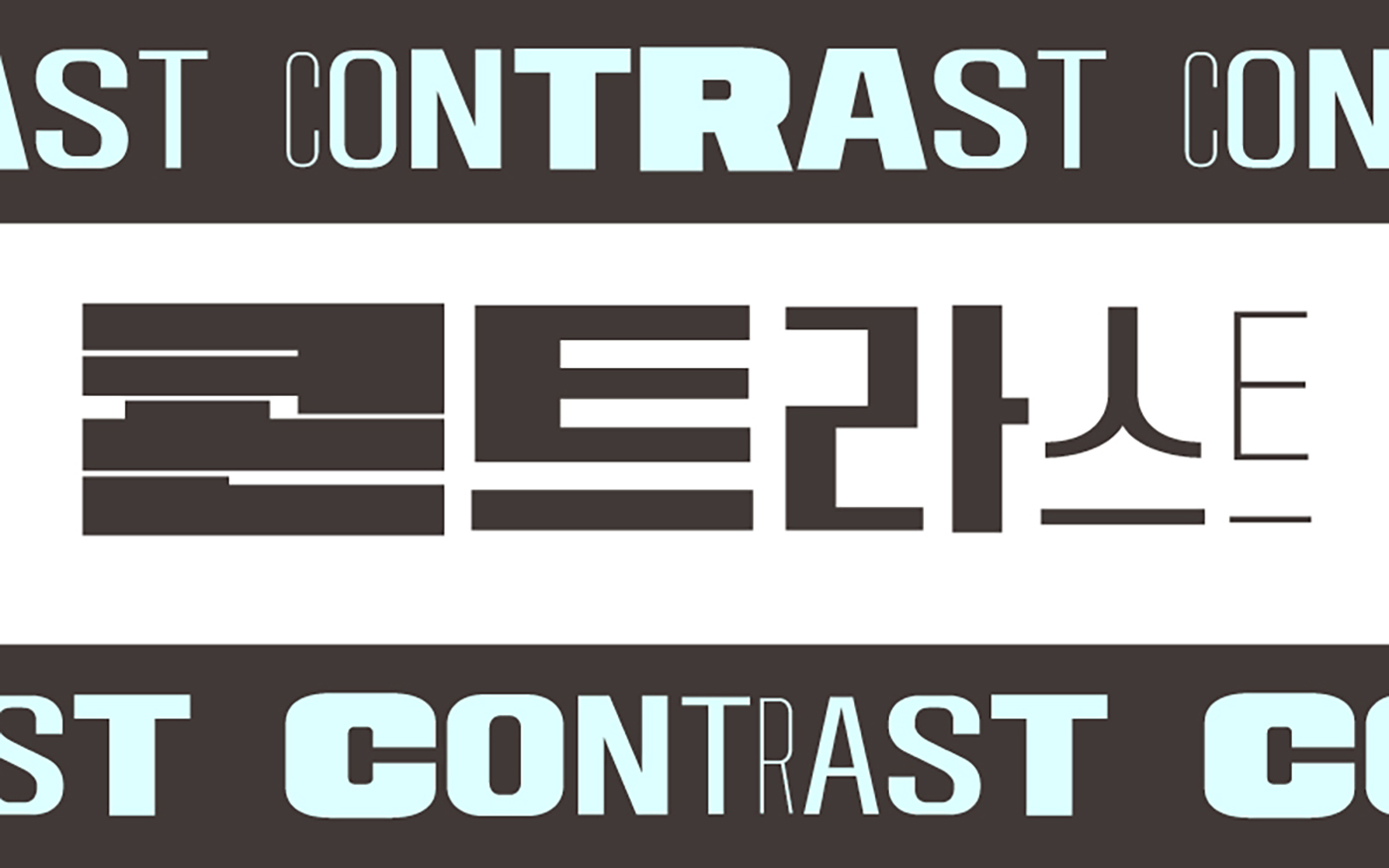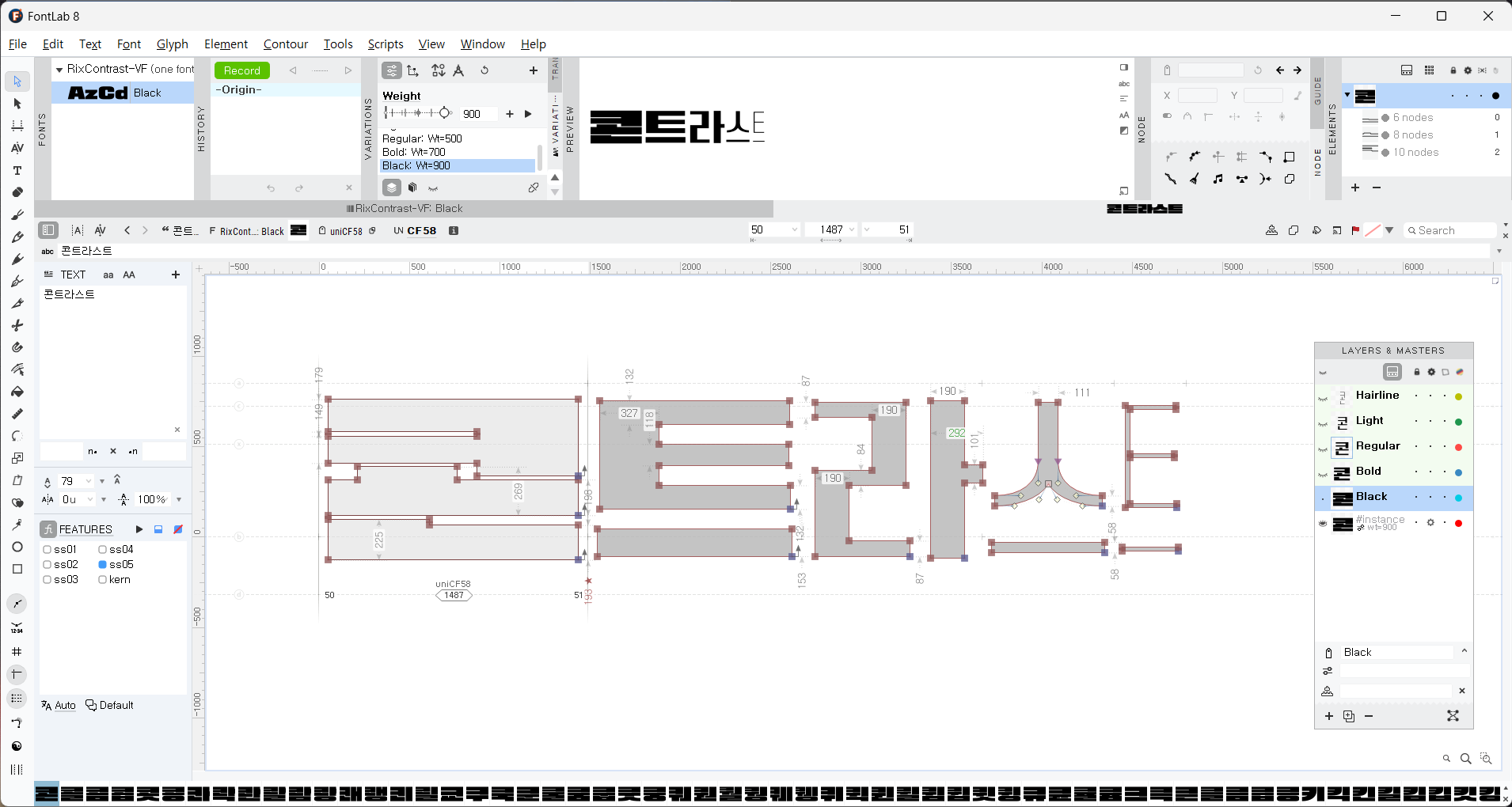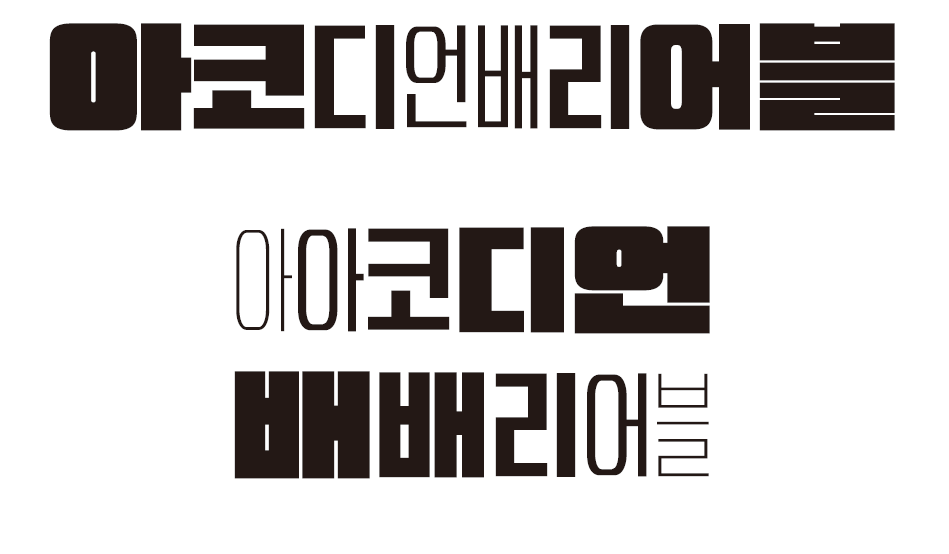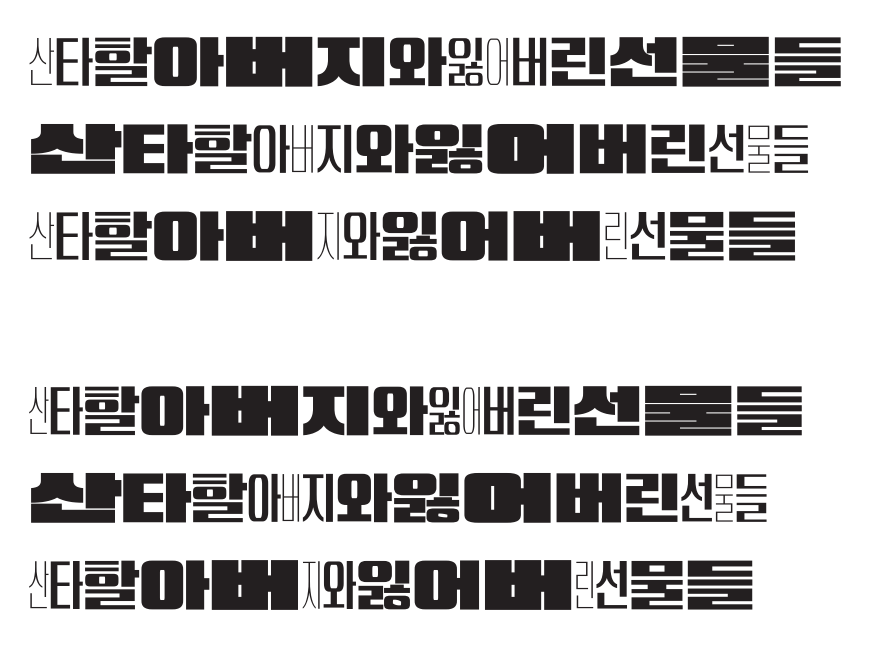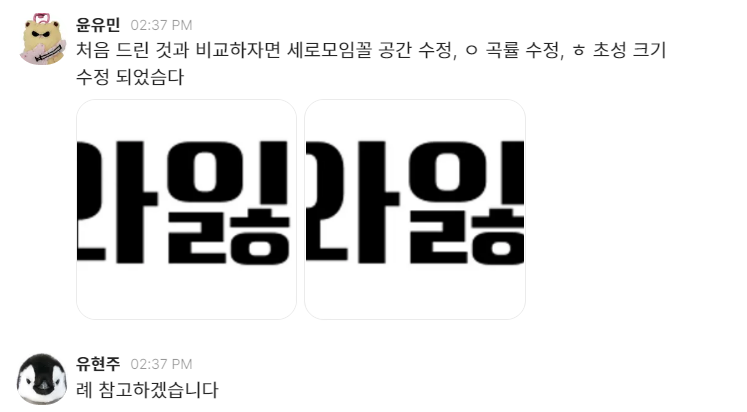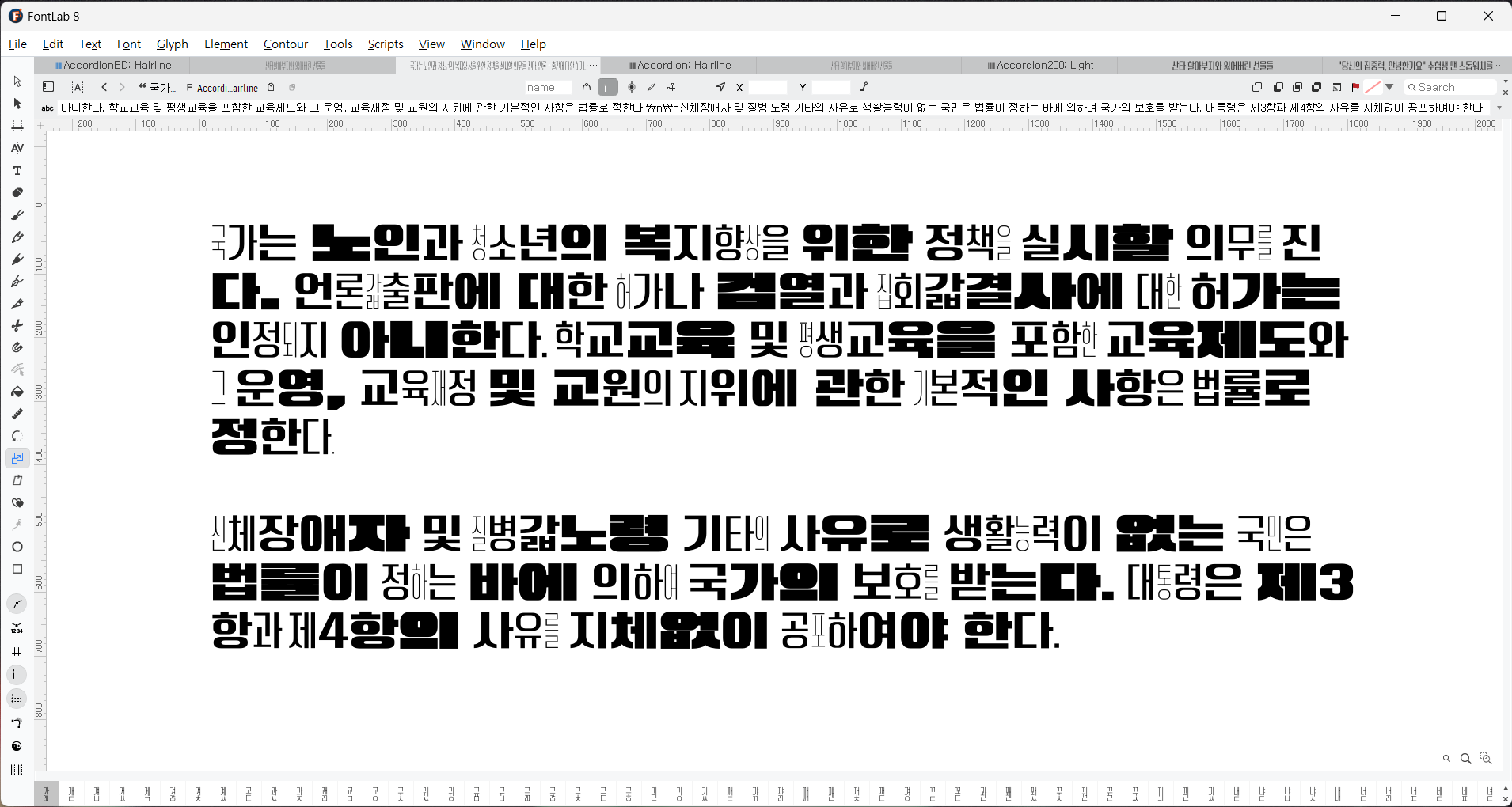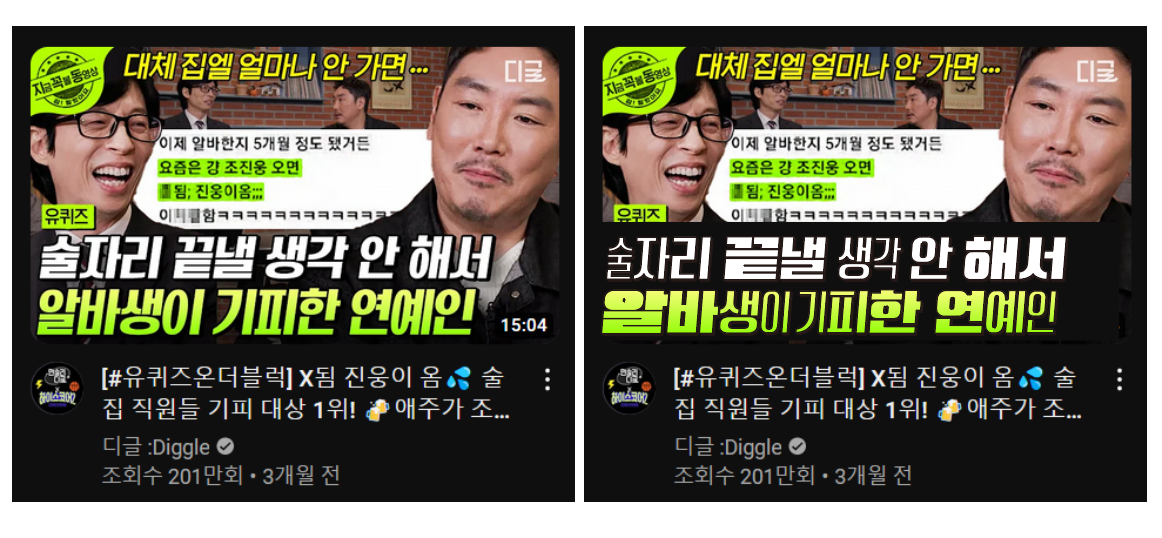
안녕하세요. 오랜만에 배리어블 서체로 돌아온 7월의 신규 폰트 「Rix콘트라스트」를 소개합니다. 이번에도 기본기 탄탄하고 지금까지 보지 못한 새로운 스타일의 배리어블 폰트 2종으로 찾아왔는데요. 어떤 폰트가 기다리고 있을지 이번 서체를 기획하고 제작한 윤유민 디자이너를 인터뷰를 통해 만나보겠습니다 :)
안녕하세요, 윤유민 디자이너님. 7월의 신서체에 대해 간단히 소개 부탁드려요!
안녕하세요, 콘트라스트-VF, 콘트라스트-Basic-VF 제작을 담당한 윤유민입니다. 유현주 디자이너님과 공동작업을 했는데 제가 인터뷰를 하게 되어 인사드려요, 3개월 만이네요!
보는 순간 임팩트가 굉장히 강하다고 느낀 폰트인데요, 어떻게 기획하게 되신 폰트인가요?
폰트릭스의 브랜드 포지션을 생각해 봤을 때, 배리어블 폰트 개발을 강점으로 하는 회사로 설정했습니다. 클라우드의 폰트들을 분석하다 보니 배리어블 폰트 초기에 많이 등장했던 얇고 좁은 글자부터 두껍고 넓은 글자까지의 극적인 변화를 갖는 폰트가 의외로(?) 없는 것을 발견했습니다.
이런 이미지는 핀터레스트 등에서 쉽게 찾아볼 수 있는데요, 실제 제작하는 과정에서 글자 하나하나의 굵기 값을 다르게 설정하는 번거로움이 있습니다. 이에 착안하여 오픈타입 기능을 추가하면 어떨까 생각했습니다. 글자의 변화가 타이핑할 때 순차적으로 나타나면 편리하고 재미있을 것 같아 오픈타입 배리어블 서체를 기획했습니다.
제작이 까다로운 배리어블 폰트, 어떤 과정을 거쳤는지?
배리어블 서체는 기존 서체보다 신경을 써야 할 부분이 많아서 제작이 까다로운 것은 사실입니다. 하지만 이미 폰트팀 내에서 잘 응용하고 있던 기능이기에, 원도 제작 시 큰 어려움은 없었어요. 출시 과정이 복잡해 기술팀에서 많은 수고를 해주셨습니다. 개인적으로 배리어블보다는 오픈타입 중 스타일 대체 기능을 처음 사용해 봐서 흥미로웠습니다. 앞서 출시된 오픈타입 배리어블 폰트, 블랙산스 VF-Wiggle을 제작한 박민우 디자이너님에게 도움을 많이 받았어요.
폰트의 매력 포인트나 가장 신경 쓴 점이 무엇인지!
박용락 디자이너님이 처음 기획했던 시안보다 극적인 변화를 주면 좋을 것 같다고 조언해 주셔서, 글자의 변화 정도를 정하는 것이 제일 고민했던 과정이었습니다. 배리어블 정도와 회색도 연구는 원도 완성 직전까지 수정에 수정을 거듭했습니다.(먼 산) 많은 우여곡절 끝에 현재의 회색도와 배리어블 변화도를 갖게 되었습니다. Basic-VF 사용 시의 완성도도 놓치지 않으려 신경을 썼습니다.
이번 서체는 유현주 디자이너님과 함께 작업을 했는데요. 사람마다 글씨체가 다르듯이 디자이너에 따라 글자의 무드와 공간이 달라질 수 있어, 웨이트 내에서의 균질한 이미지를 위해 많은 소통을 하며 글자를 다듬었답니다. 오픈타입에 낯선 사용자들을 고려하여 오픈타입이 적용된 버전(Rix콘트라스트-VF)과 기본적인 버전(Rix콘트라스트-Basic-VF)으로 나누어 출시하게 되었습니다. 각 버전에 따라 가벼운 장체와 무거운 평체의 변화도를 조절하는 재미가 있을 것입니다!
Rix콘트라스트-VF와 Rix콘트라스트-Basic-VF, 각각의 특징을 좀 더 자세히 설명해 주신다면?
콘트라스트 VF는 BasicVF의 굵기 세트가 순차적으로 타이핑되는 오픈타입 배리어블 폰트입니다. 한 글줄 내에서 글자들이 좌우로 확장하거나 축소되어 강렬하고 재미있는 인상을 표현할 수 있습니다. 글줄에서 느껴지는 회색도의 변화를 하루의 흐름으로 비유하여 축의 이름을 'Day'로 지었고, 총 3종의 인스턴스를 제공합니다. Rix콘트라스트-VF 바로가기
콘트라스트-Basic-VF는 좁고 얇은 웨이트에서 넓고 무거운 웨이트까지의 변화를 제공하는 배리어블 폰트입니다. 일반적인 배리어블의 축인 장평과 굵기를 조합하여 더욱 극적인 변화를 꾀했습니다. 5종의 인스턴스를 가지며 'Weight' 축을 움직여 섬세한 조정을 할 수 있습니다. Rix콘트라스트-Basic-VF 바로가기
어떻게, 어디에 사용하면 좋을지?
콘트라스트-VF는 주목성이 크게 필요한 유튜브 섬네일이나 숏폼 타이틀 등에 추천하는 폰트입니다. 직선으로 깔끔하게 떨어지는 획의 형태를 가지고 있어 그래픽 스타일을 적용했을 때 궁합이 꽤 좋다고 느꼈어요. 회색도의 변화에 따라 글줄에 볼륨감이 생겨 옵아트* 같은 느낌도 있어서, 글자만으로 착시 효과를 주고 싶을 때(?) 사용해도 좋을 것 같아요. 글자 수가 5자 이상일 때 진정한 힘을 발휘하므로.. 되도록 단어가 아닌 문장에 사용하시는 것을 권장합니다.
콘트라스트-Basic-VF는 꽉 찬 네모의 골격으로 활용도가 높아 영상 자막이나 패키징 등 제목용 폰트가 필요한 여러 분야에서 사용해 보는 걸 추천합니다. 웨이트에 따라 달라지는 인상을 활용하여 어조의 강약을 크게 표현하는 포스터 등에 사용하기에도 좋을 것 같아요.
*옵아트(Optical Art): 추상적 무늬와 색상을 반복하여 표현함으로써 실제로 화면이 움직이는 듯한 착각을 일으키게 하는 미술
재미있게 배리어블, Rix콘트라스트-VF
Rix콘트라스트-VF는 글자 하나하나에 다른 폭과 두께를 적용하여 디자인한 서체입니다. 인터뷰에서 언급했듯이 글줄에서 느껴지는 회색도의 변화를 하루의 흐름으로 비유하여 축의 이름을 Day로 지었는데요, 그에 맞게 Morning - Noon - Night 세 가지 큰 인스턴스(instance)로 구성되어 있습니다.
Day 축을 통해 글자의 굵기와 폭이 순차적으로 다르게 나타나는 효과를 조절할 수 있는 배리어블 폰트입니다. 한 글줄 내에서 글자들이 좌우로 확장되거나 축소되면서 강렬하고도 재미있는 인상을 줍니다.
[포토샵 - OpenType - 문맥대체] 효과를 통해 적용 가능합니다.
통일성 있는, Rix콘트라스트-Basic-VF
베이직 버전인 Rix콘트라스트-Basic-VF는 얇고 좁은 글자부터 두껍고 넓은 글자까지 Weight 축을 통해 굵기와 폭을 동시에 조절합니다. 원래의 글자 하나하나에 다른 폭이 적용되는 콘트라스트-VF와는 또 다른 매력이 있죠.
Hairline - Light - Regular - Bold - Black 다섯 개의 인스턴스로 구성되어 있으며, 배리어블 축을 통해 그 안의 수많은 굵기와 폭을 조정할 수 있습니다.
Weight 축으로 편리하게 글자의 폭과 두께를 한 번에 조절할 수 있습니다. 통일감 있는 서체로 표현할 수 있고, 좁고 가벼운 장체 느낌부터 강하고 강렬한 인상까지 다채로운 효과를 주기에 좋습니다.
이렇게 활용해 보세요📌
콘트라스트-VF의 강한 임팩트나 독특한 형태는 디자인 그 자체로 사용해도 좋을 것 같아요. 이렇게 포스터 디자인에 텍스트만으로도 ART 그 자체가 되는 매직🪄
콘트라스트-Basic-VF는 하나의 서체로 다양한 느낌을 표현할 수 있어 그래픽적 활용도가 높습니다. 하나의 큰 틀 안에서 통일감이 있으면서도 폭, 굵기의 변화로 텍스트마다 다른 느낌을 주어 풍성한 디자인 연출 가능합니다.